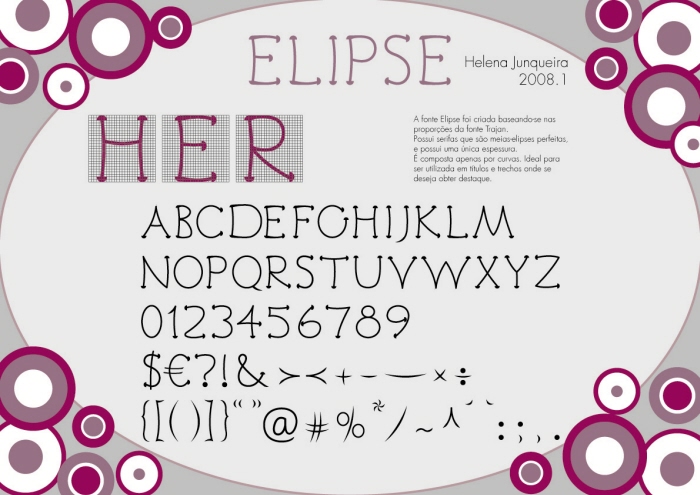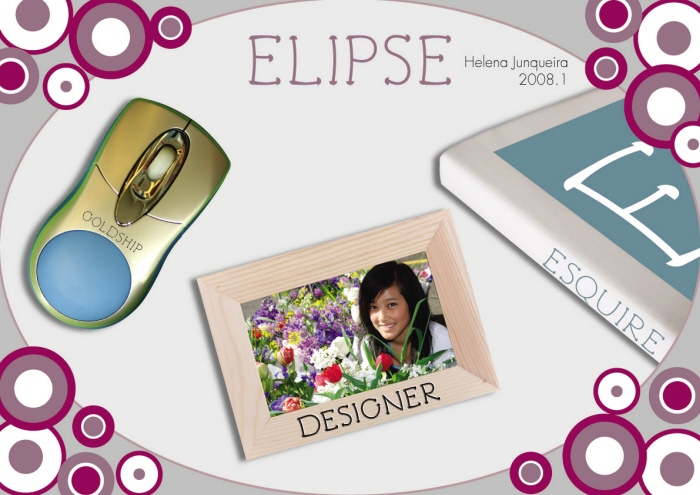
Criacao do tipo "Elipse" - A fonte Elipse foi criada baseando-se nas proporcoes da fonte Trajan.
Possui meias-elipses como serifa e apresenta uma unica espessura.
E composta apenas por curvas.
Ideal para ser utilizada em titulos e trechos onde se deseja obter destaque.
Aplicacoes do tipo Elipse - Possui meias-elipses como serifa e apresenta uma unica espessura.
E composta apenas por curvas.
Ideal para ser utilizada em titulos e trechos onde se deseja obter destaque.